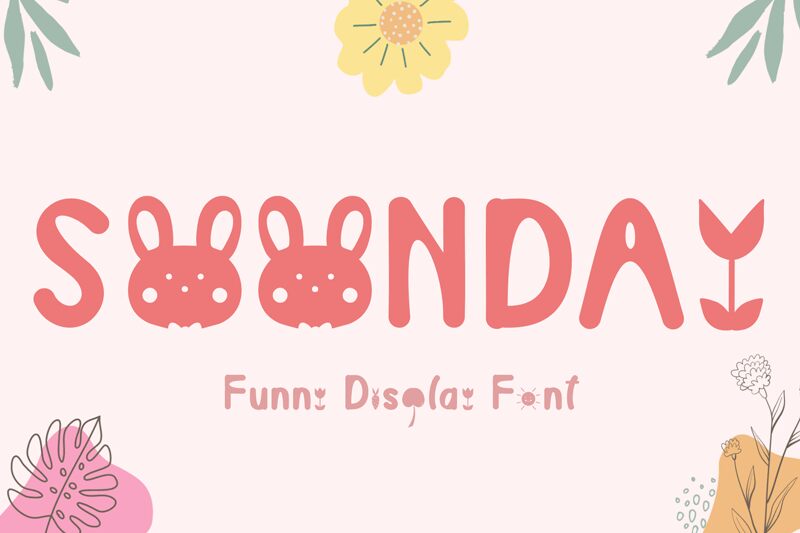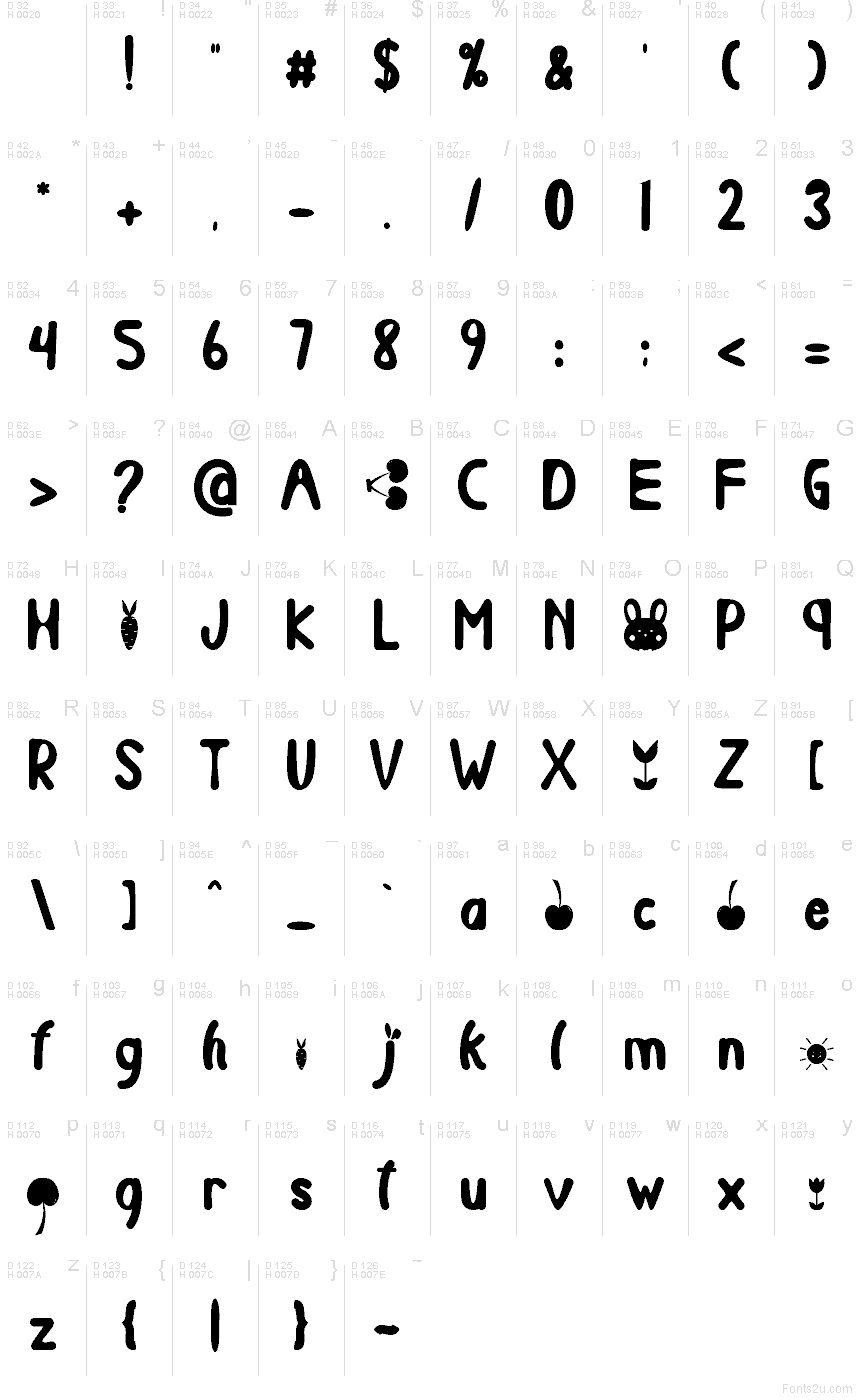
Soonday
Soonday de Yoga Letter es una tipografía decorativa gratuita para titulares, con formas redondeadas y amigables que integran un motivo solar en su diseño. Las letras se combinan con pequeños soles radiantes, lo que aporta al conjunto un carácter artesanal y luminoso sin resultar recargado.
Soonday funciona a la perfección en carteles, folletos de verano, identidad visual de cafeterías, papelería infantil y gráficos para redes sociales donde se busca un elemento visual potente que sostenga toda la composición. Esta fuente gratuita también es ideal para packaging, encabezados de invitaciones y logotipos, ya que los detalles solares integrados añaden un acento decorativo claro sin necesidad de añadir ilustraciones extra.